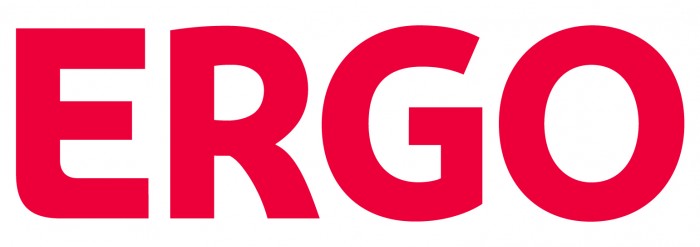
Welche Schriftart ist das (ERGO)?
Ich würde mal ganz einfach behaupten, dass diese Schrift genau aus 4 Glyphen besteht E, G, O und R, und die hat der Gestalter dieses Logos gezeichnet, ohne Stunden seiner Arbeitszeit in eine Schriftsuche zu verschwenden. Hierdurch wird ja ein Logo einzigartig.